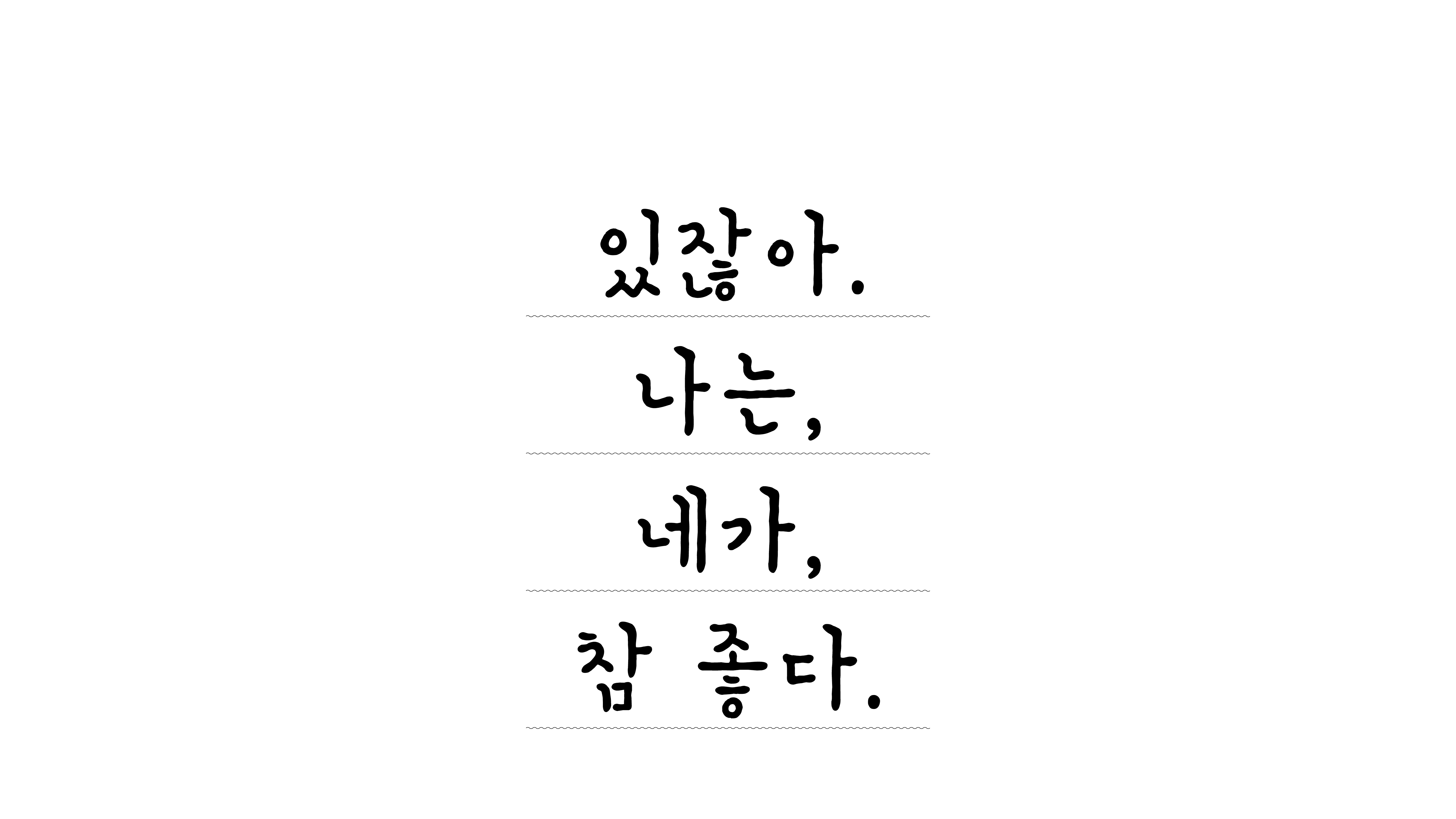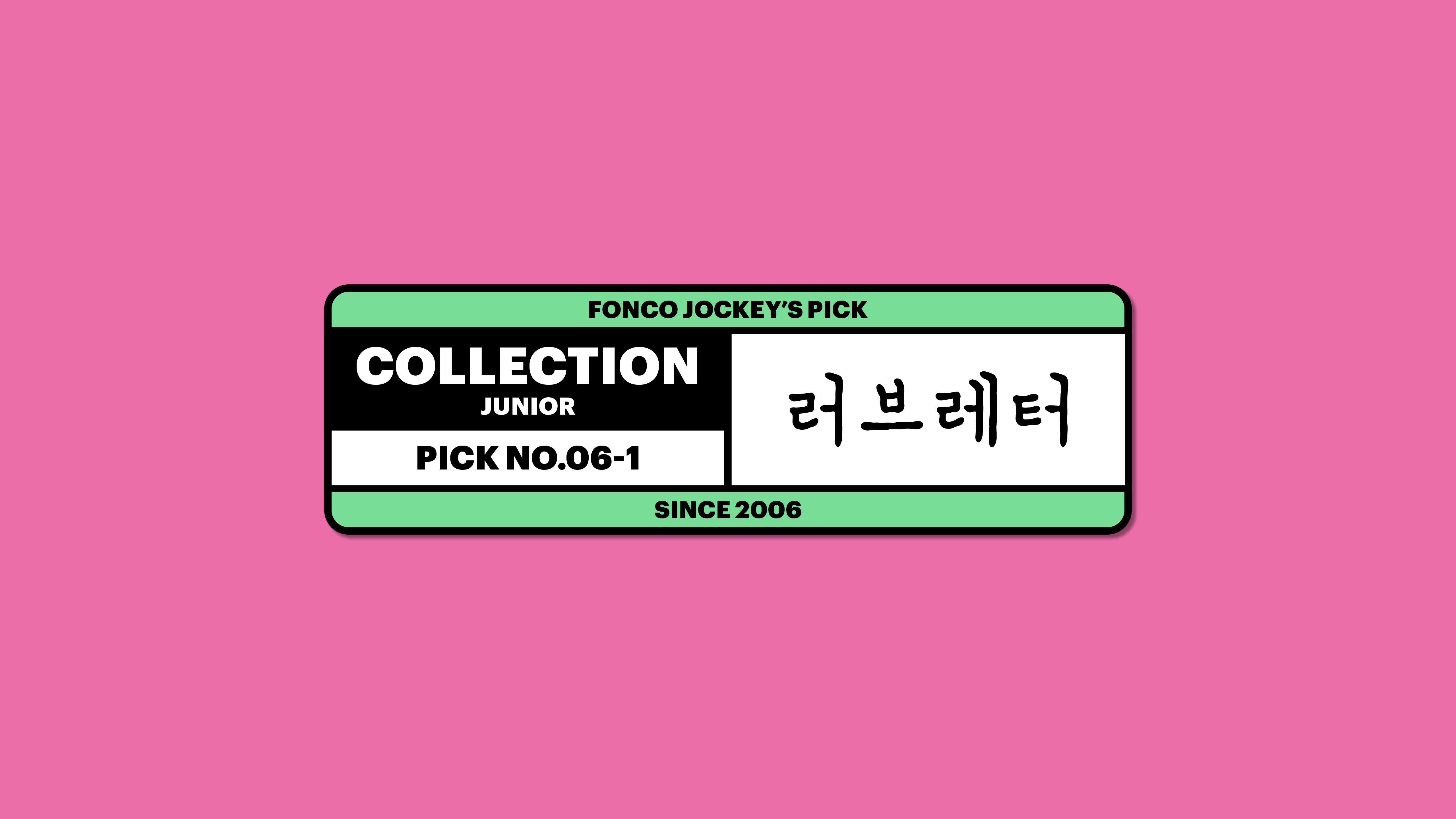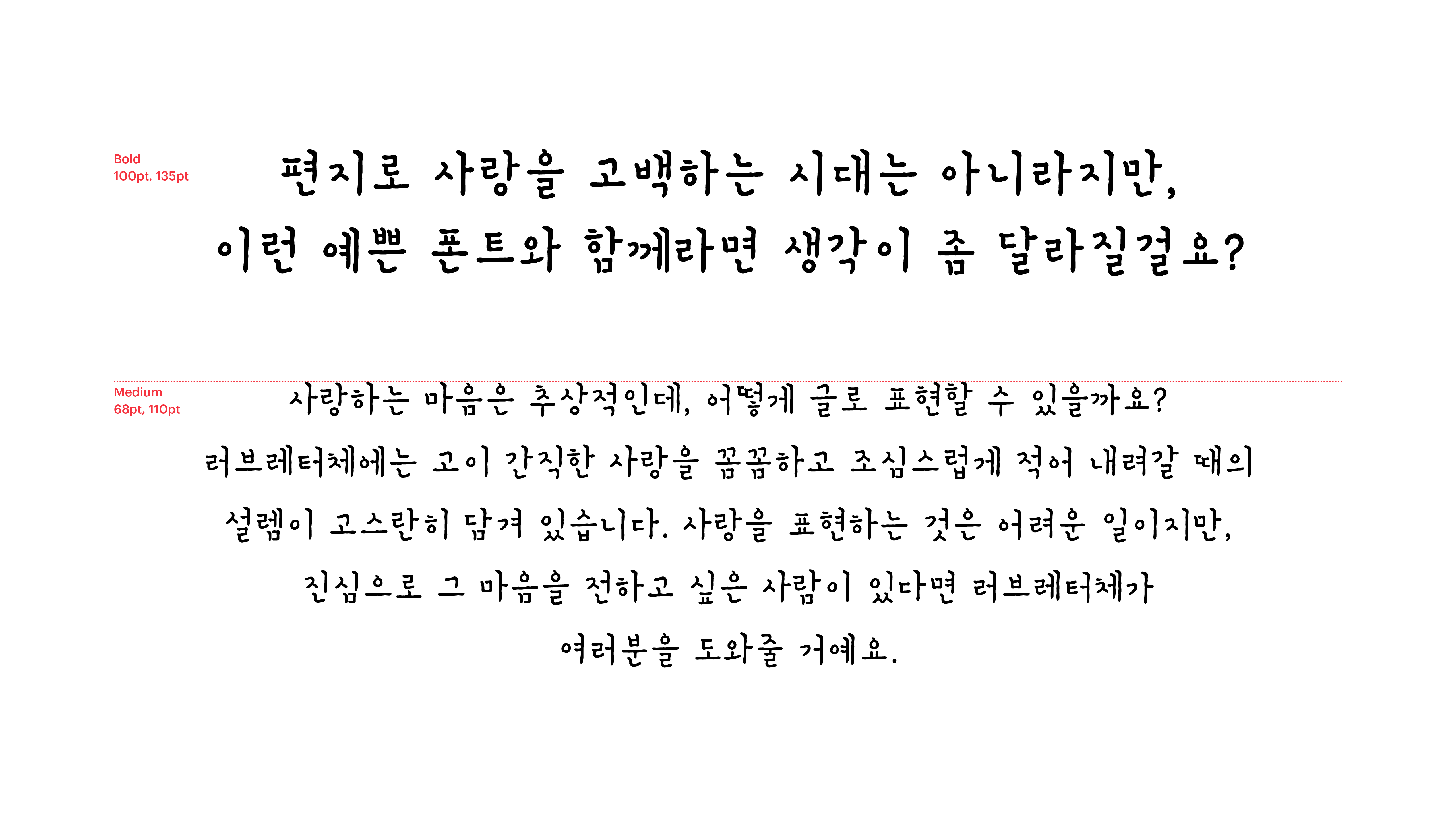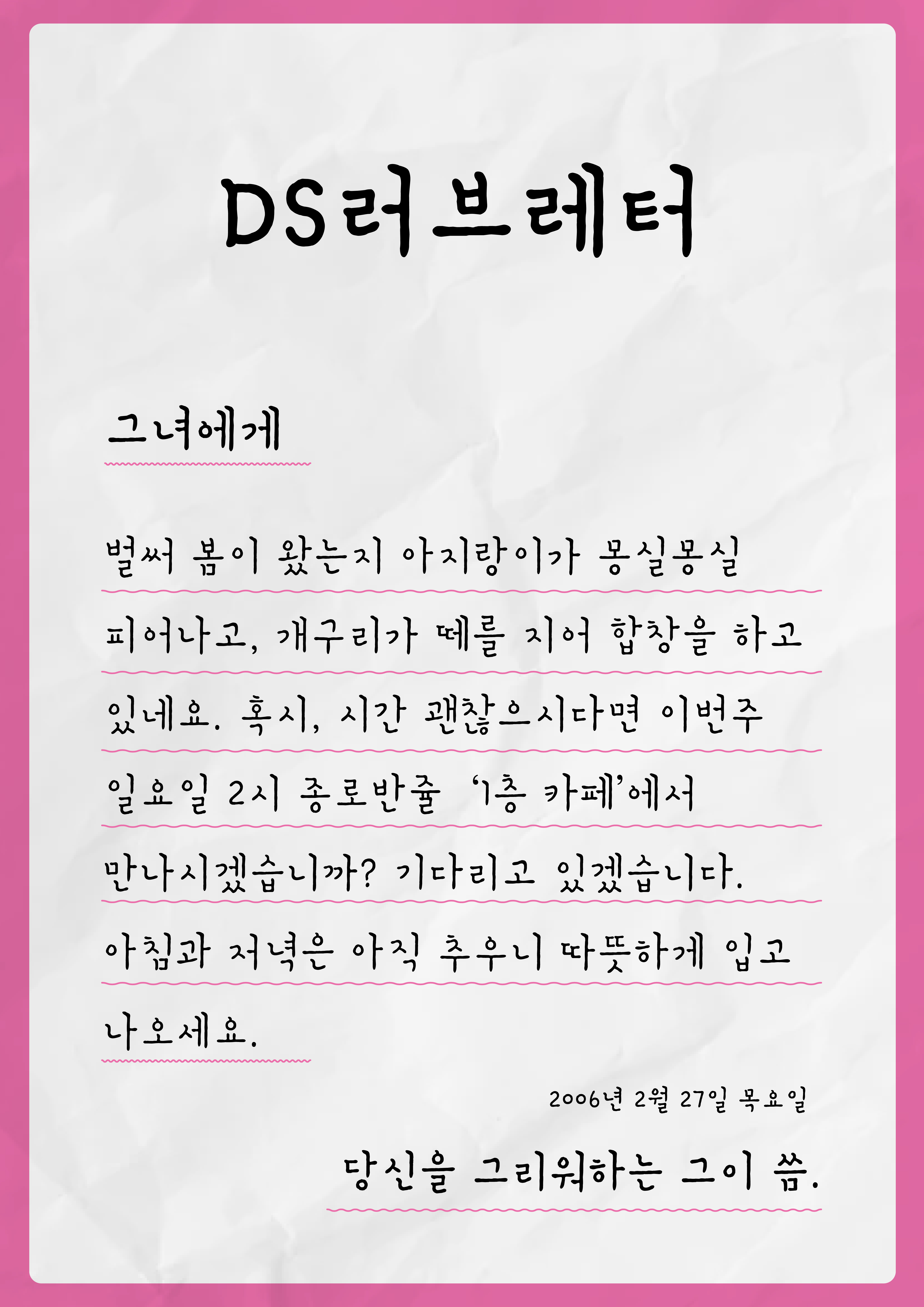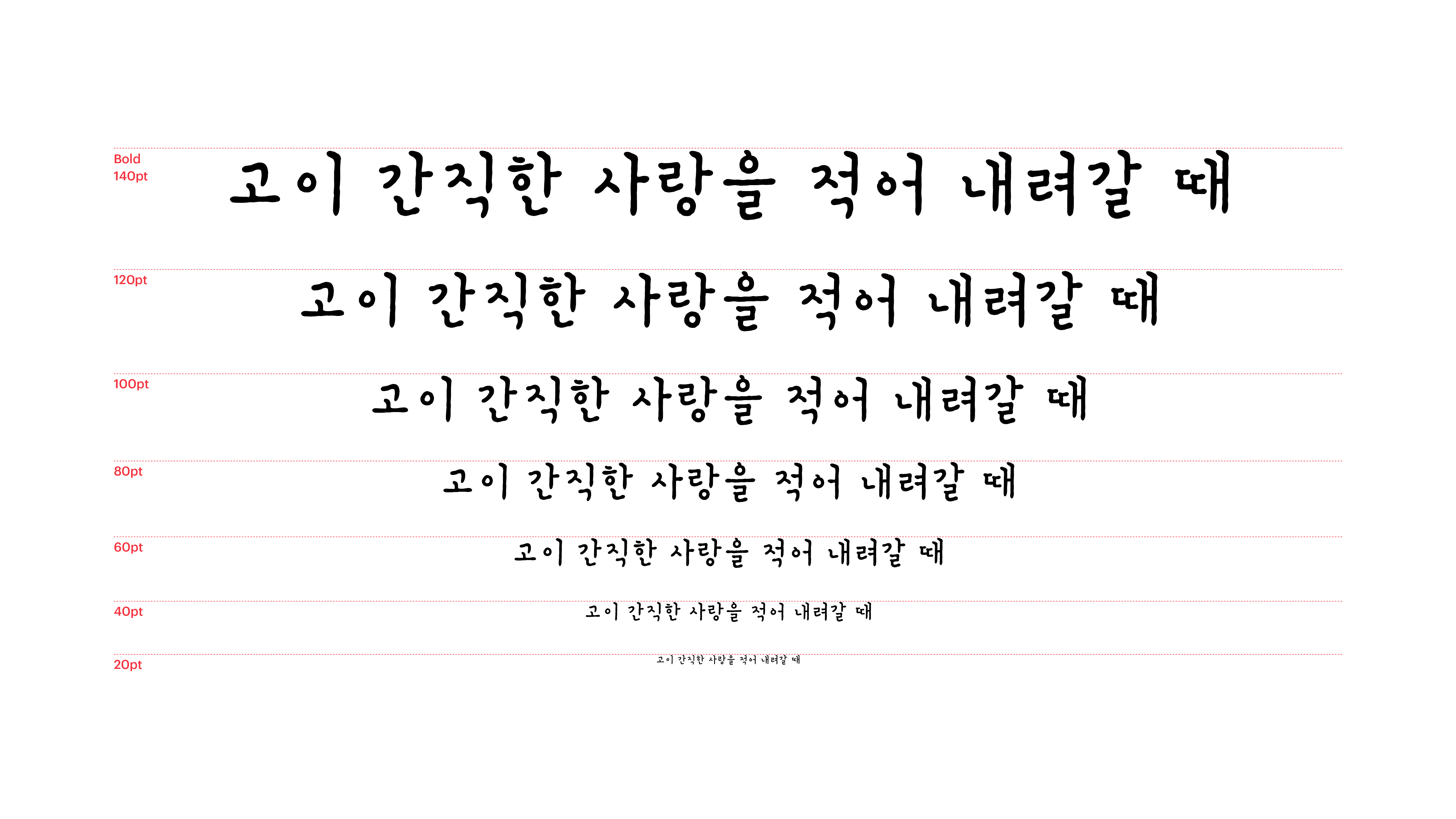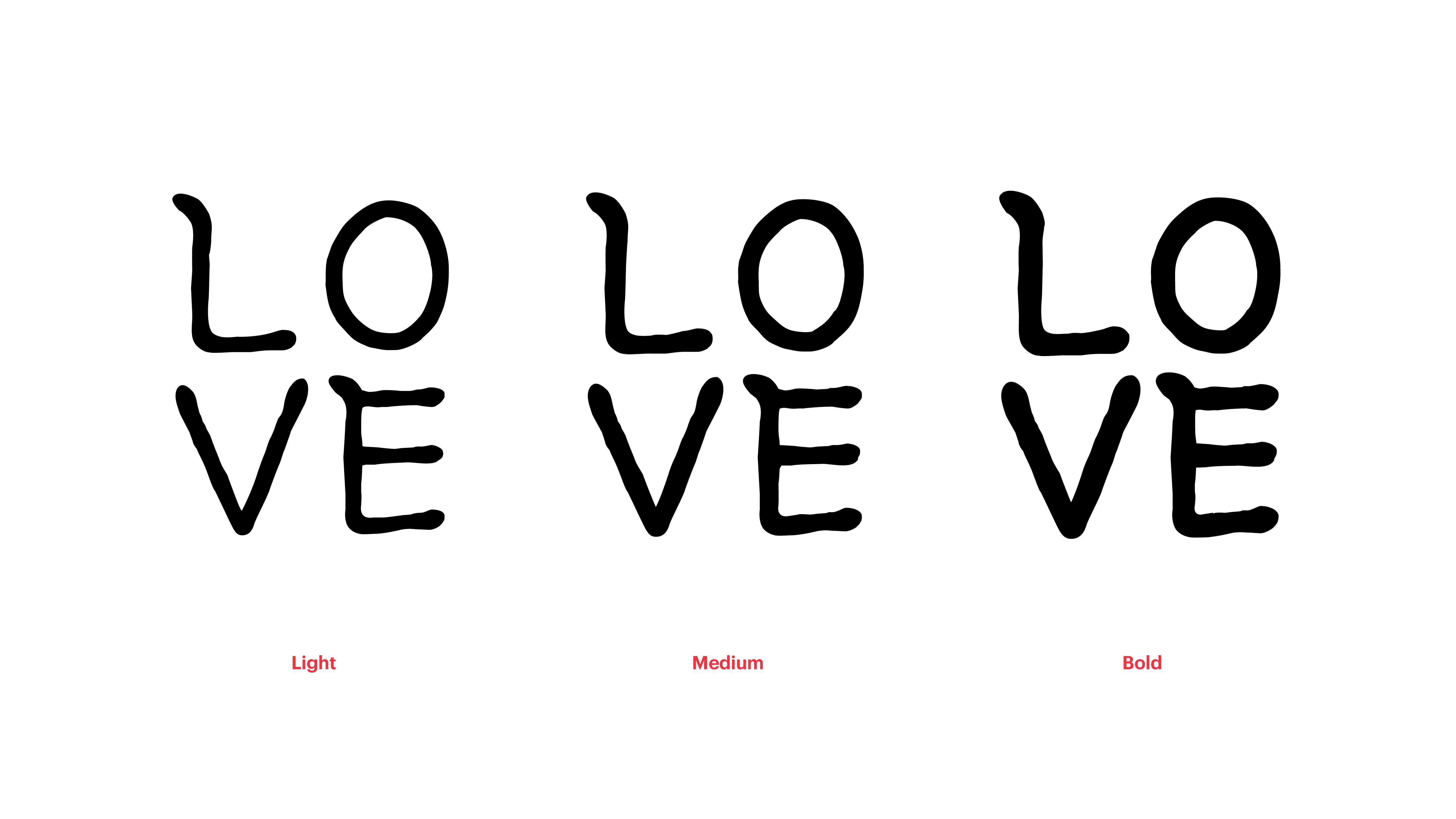
러브레터
Yoon 러브레터
사랑하는 마음은 추상적인데, 어떻게 글로 표현할 수 있을까요? 러브레터체에는 고이 간직한 사랑을 꼼꼼하고 조심스럽게 적어내려갈 때의 설렘이 고스란히 담겨 있습니다. 사랑을 표현하는 것은 어려운 일이지만, 진심으로 그 마음을 전하고 싶은 사람이 있다면 러브레터체가 여러분을 도와줄 거예요.